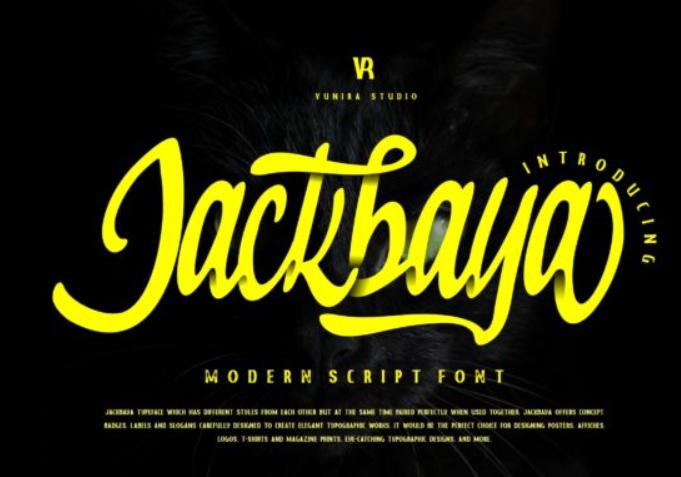
Jackbaya - шикарный утонченный шрифт, излучающий изысканность и элегантность. Его стильные альтернативы и лигатуры делают этот шрифт идеальным для любого проекта.